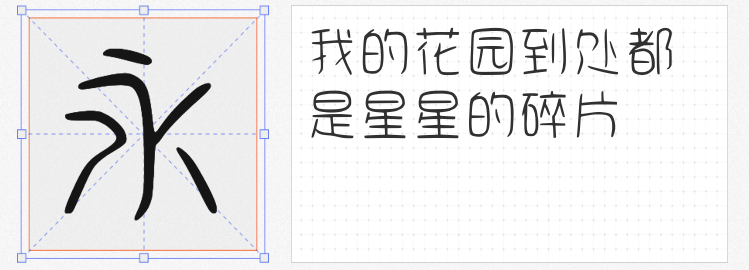
在母婴、儿童用品的设计中,字体是传递温暖与童趣的第一张名片。如何让文字既充满亲和力,又兼具艺术性与实用性。本文精选四款免费商用字体,它们以柔和线条、灵动笔触与趣味结构,为母婴品牌、儿童绘本、玩具包装等场景注入治愈能量。
字体家AI造字柒恒是一款由AI生成的字体。其线条如婴儿肌肤般细腻流畅,笔画转折处自然过渡,传递出“零负担”的视觉安全感。这款字体适用于母婴产品包装、儿童绘本标题或早教APP界面,以温润质感营造“被温柔包裹”的视觉体验,让品牌成为孩子成长路上的无声陪伴者。
也字工厂小石头体以“软萌”为设计灵魂,字形如Q弹果冻般充满弹性。笔画粗细对比强烈却不突兀,软笔书写的洒脱感与圆润特征结合,让文字自带“蹦跳”的动态感。这款字体是儿童零食包装、幼儿园活动海报或卡通IP衍生品的“氛围制造机”,其率真风格能瞬间拉近与孩子的距离,让设计充满“想捏一捏”的冲动。
平方张亚玲黑方体打破黑体的严肃感,在几何结构中融入卡通元素。笔画末端的小圆角、局部的夸张变形与适度的留白,让字体既保留黑体的稳重,又兼具卡通体的俏皮。这款字体适合儿童服饰标签、益智玩具说明书或早教机构宣传页,以“可盐可甜”的气质平衡专业性与趣味性,让信息传递更生动。
字制区喜脉喜欢体以手写笔触为底色,笔画如孩童涂鸦般自由灵动。其文艺气质与随性结构,让文字成为“会呼吸的诗句”。这款字体适合儿童摄影工作室标题、绘本扉页寄语或亲子活动海报,以少字数的大标题形式呈现时,能瞬间抓住视线,传递“记录成长”的温暖仪式感。
母婴儿童设计的核心,是让文字成为情感的容器。这四款免费商用字体以圆润、Q弹、趣味与自由为关键词,为设计师提供了多元选择。当创意需要拥抱童心时,它们或许就是那把打开童趣世界的钥匙。